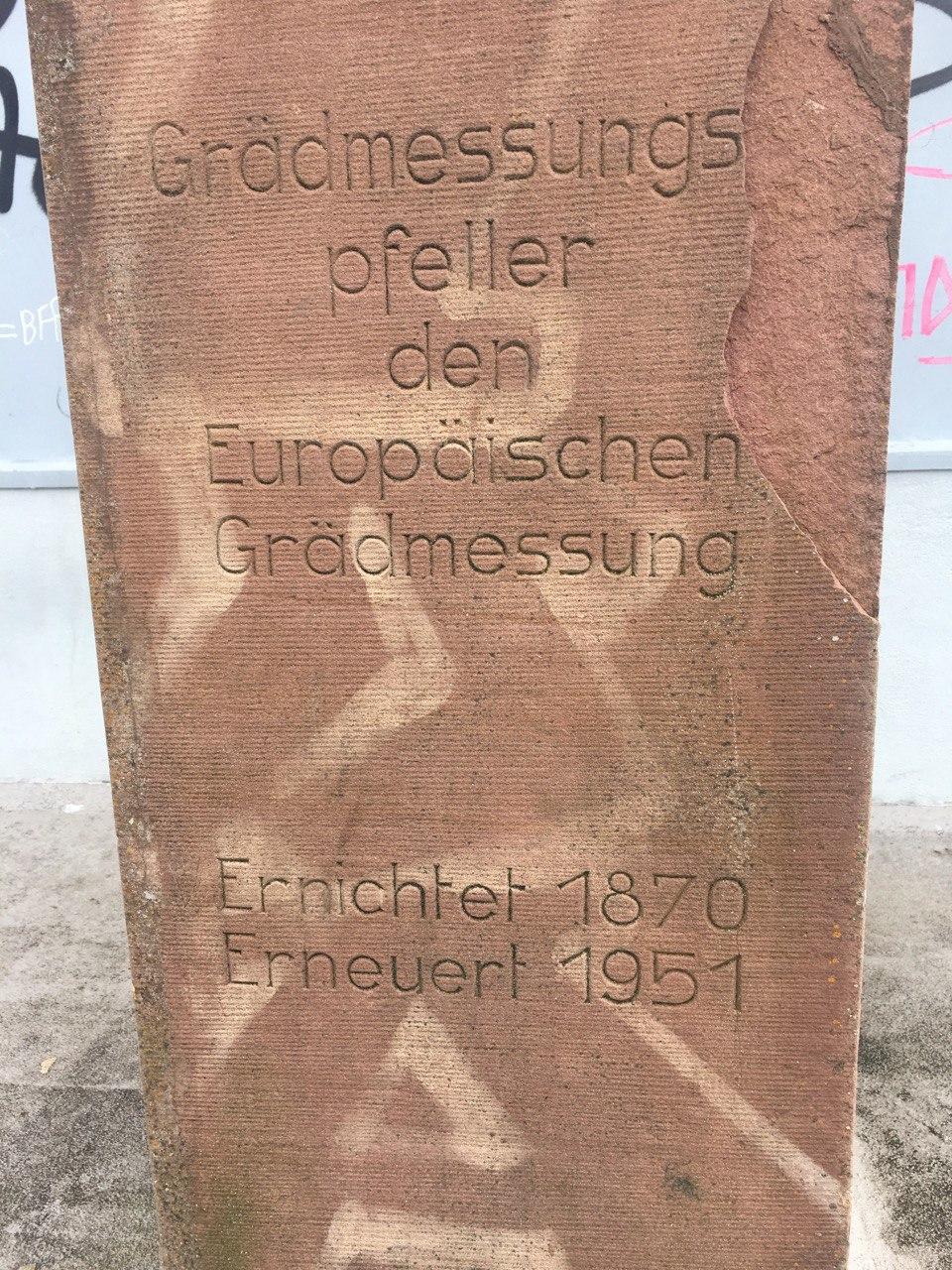
Suche Gravur-Schrift um 1950 (?)
ich suche den Namen (oder Ähnliche) dieser Schriftart von einem Poller aus Durlach in der Nähe von Karlsruhe.
sie müsste wohl von 1951 sein. Ich weiss nicht genau wie zu der Zeit graviert wurde, das ganze wirkt aber schon nach einer gezeichneten Schrift.
Ich habe ein wenig nach Gravur-Schriften gesucht jedoch nicht wirklich etwas gefunden was in die Nähe kommt.
Generell bin ich recht interessiert an Monoline/Gravur Schriften also falls jemand mehr Infos in die Richtung hat würde ich mich freuen.